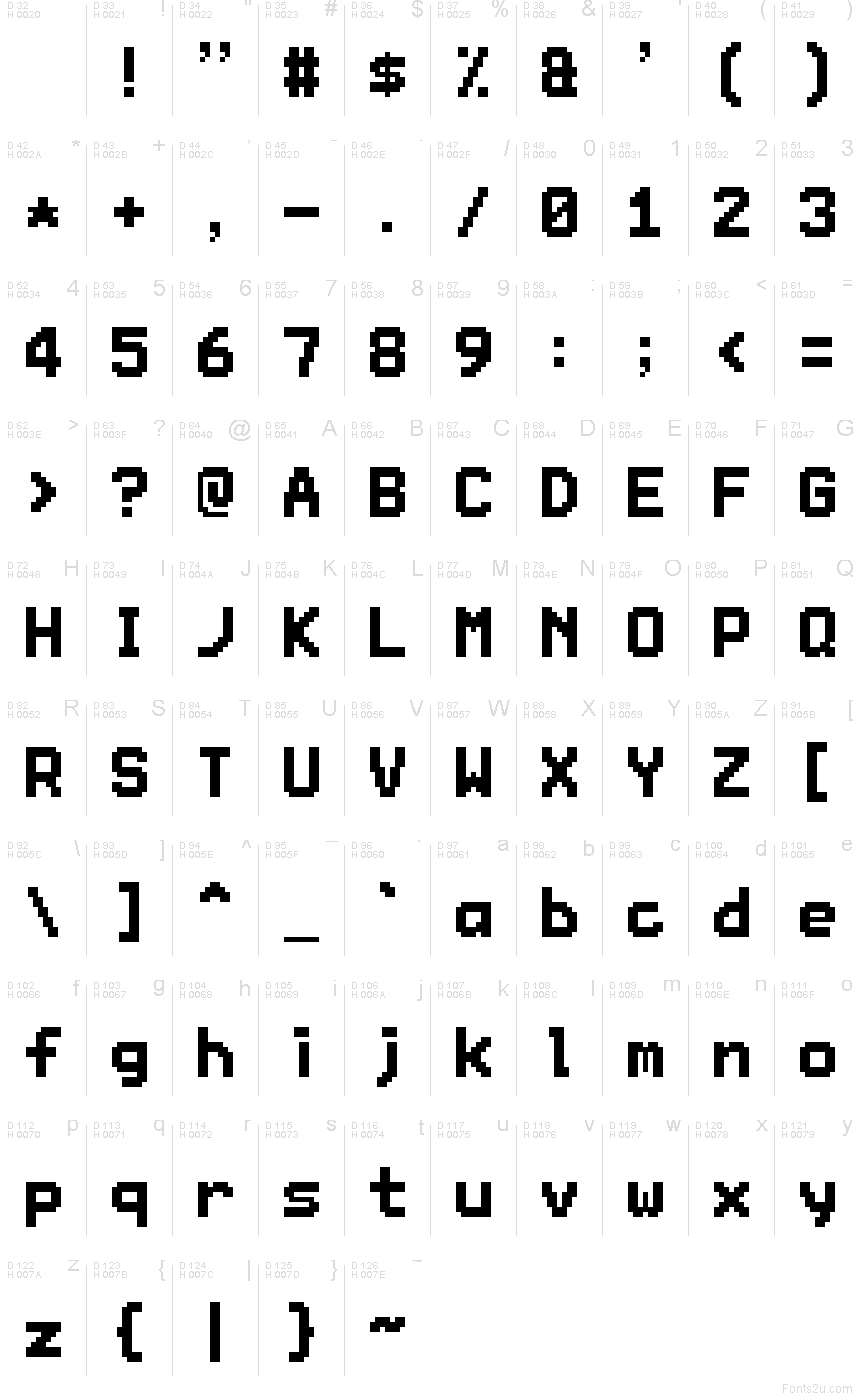
Tengoku od TLF je bezplatné pixelové písmo vytvořené z hustých, čtvercových tvarů. Jeho písmena využívají pevné pravé úhly, kompaktní proporce a ostře řezané vnitřní mezery. Konstrukce s nízkým rozlišením nepůsobí křehce, nýbrž záměrně a masivně.
Arkádové hry a elektronická hudba poskytují tomuto přísnému digitálnímu stylu přirozené prostředí. Hodí se také pro grafiku rozhraní, plakáty na akce a streetwearové oblečení s futuristickým či industriálním nádechem. Tyto opakující se obdélníkové výřezy mohou v celém vizuálu připomínat panely obrazovek, vzory obvodů a modulární ilustrace.